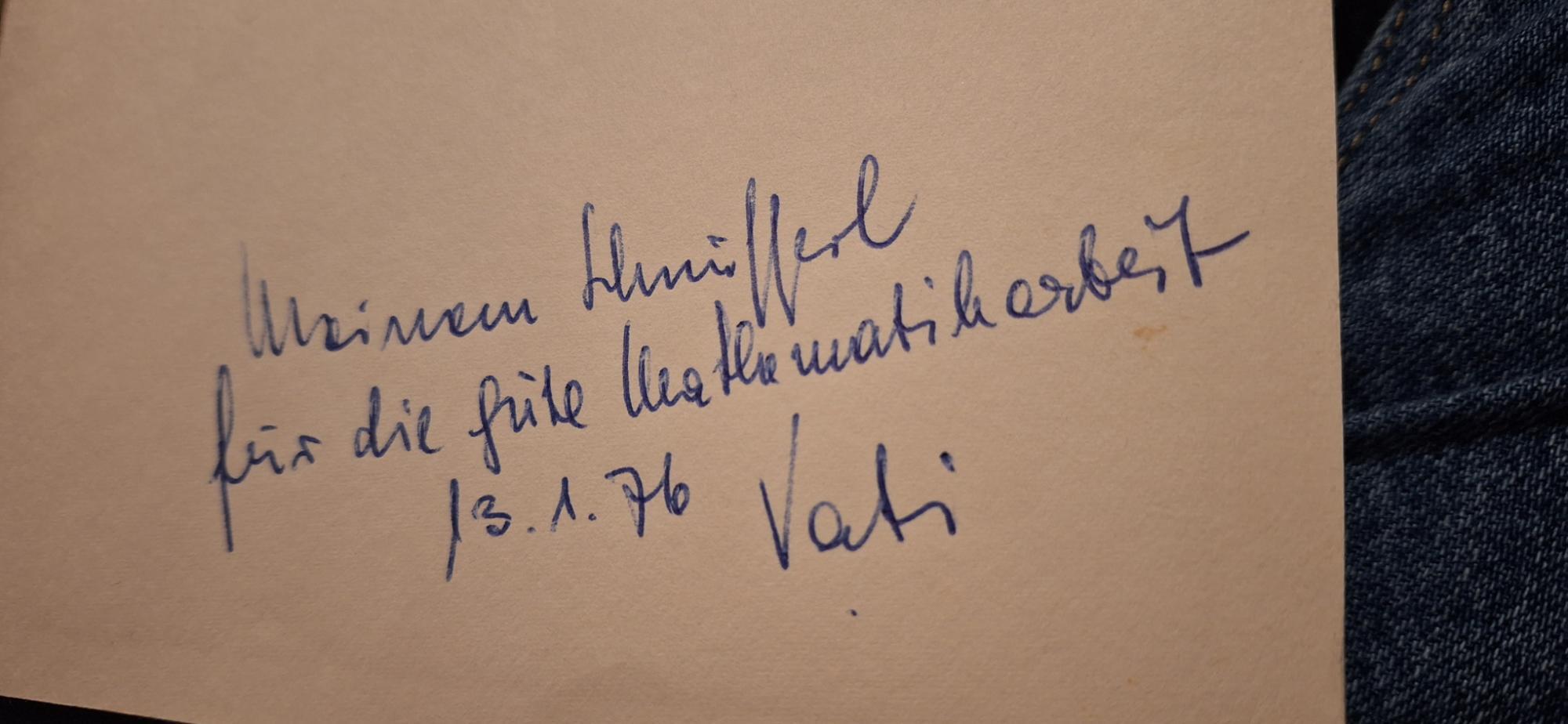
Bitte um Entzifferung 1976
Ich bin ganz neu hier, aber wollte jetzt schon seit einer Weile wissen, was das Wort im Bild bedeutet. "Meinem ....", steht in einem Buch, dass ich gebraucht gekauft habe. Der Text geht weiter mit "für die gute Mathemathikarbeit 13.1.76". Ich fand es einfach so süß, dass ich etwas neugierig geworden bin bezüglich des Namen des Beschenkten:) Es handelt sich sehr wahrscheinlich um einen Eigen- bzw. Spitznamen. Vielleicht wisst ihr es ja!
Schnufferl?
Ich glaube eher nicht, oder?
Der Punkt über dem Text scheint möglicherweise ein "i" anzudeuten?
Der Punkt ist ein Strich und der Strich wurde handschriftlich üblicherweise darüber gesetzt, um da u vom n unterscheiden zu können.
Das u mit Strich darüber entspringt der Sütterlin-Schrift:
Meine Mutter (geb. 1936) schreibt das u noch heute mit Strich darüber, damals wurde es in der Schule so gelehrt.
Mich wundert die letzte Zeile ...
Ein Strich zur Verdoppelung des m und n konterkariert ja die Unterscheidung n vs. u?! Eigentlich kenne ich diese Verwendung nur in Druckschriften (fast nur beim m, seltener beim n), nicht aber in Handschriften ...
Das u hat eigentlich einen Bogen, wie oben im Bild zu sehen. Handschriftlich kenn ich den aber nur (von meinen Eltern) als Strich, nicht als Bogen. Gschlampert geschrieben halt. Den Doppelungsstrich hat meine Mutter beim n ebenfalls oft gemacht (beim m komischerweise nicht), der sah in der Tat so aus wie das u. Ergab sich aber immer aus dem Kontext, was gemeint war.